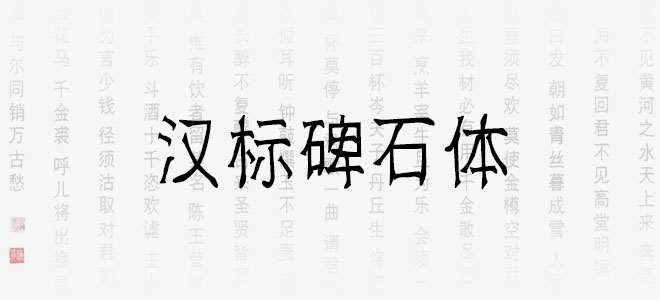
漢標(biāo)碑石體是一款描述歷史、詮釋滄桑、抱樸守靜、彰顯耐力的排版文字,同時(shí)也是古今語境的接引者,適合應(yīng)用于藝術(shù)設(shè)計(jì)、平面宣傳、包裝印刷、圖形設(shè)計(jì)、網(wǎng)頁設(shè)計(jì)、書法字帖等領(lǐng)域,歡迎喜歡漢標(biāo)碑石體的朋友前來下載使用。
漢標(biāo)碑石體字體